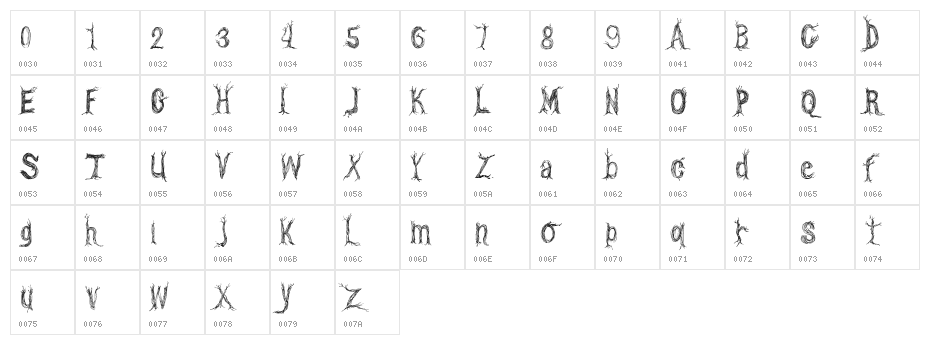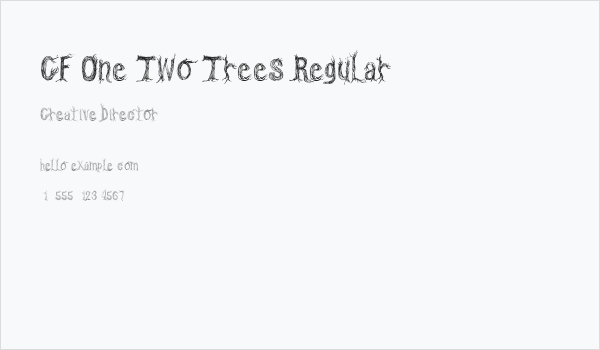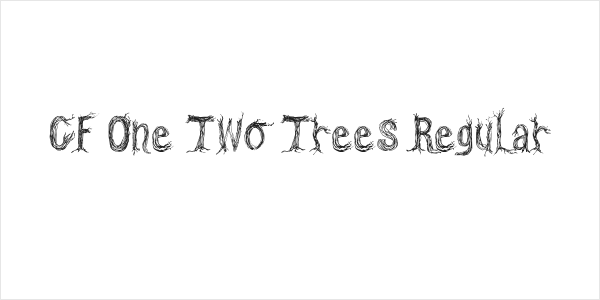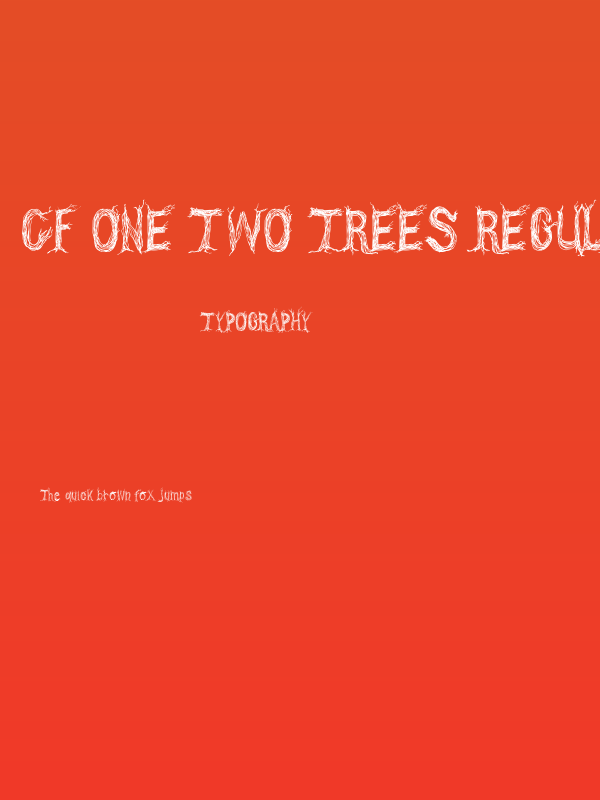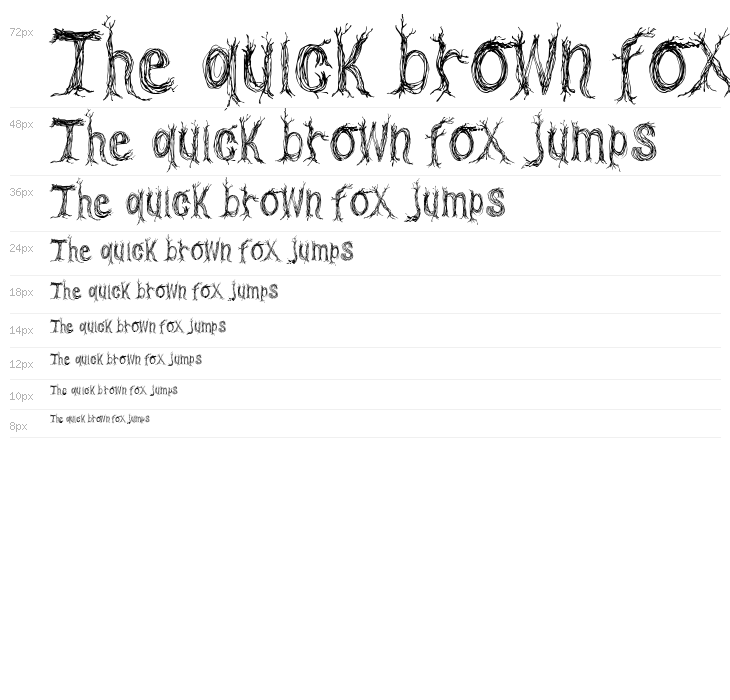
CF One Two Trees Regular Font
| Vorgeschlagene Projekte | Ideal for nature-themed designs, fantasy book covers, environmental campaigns, or Halloween decorations. |